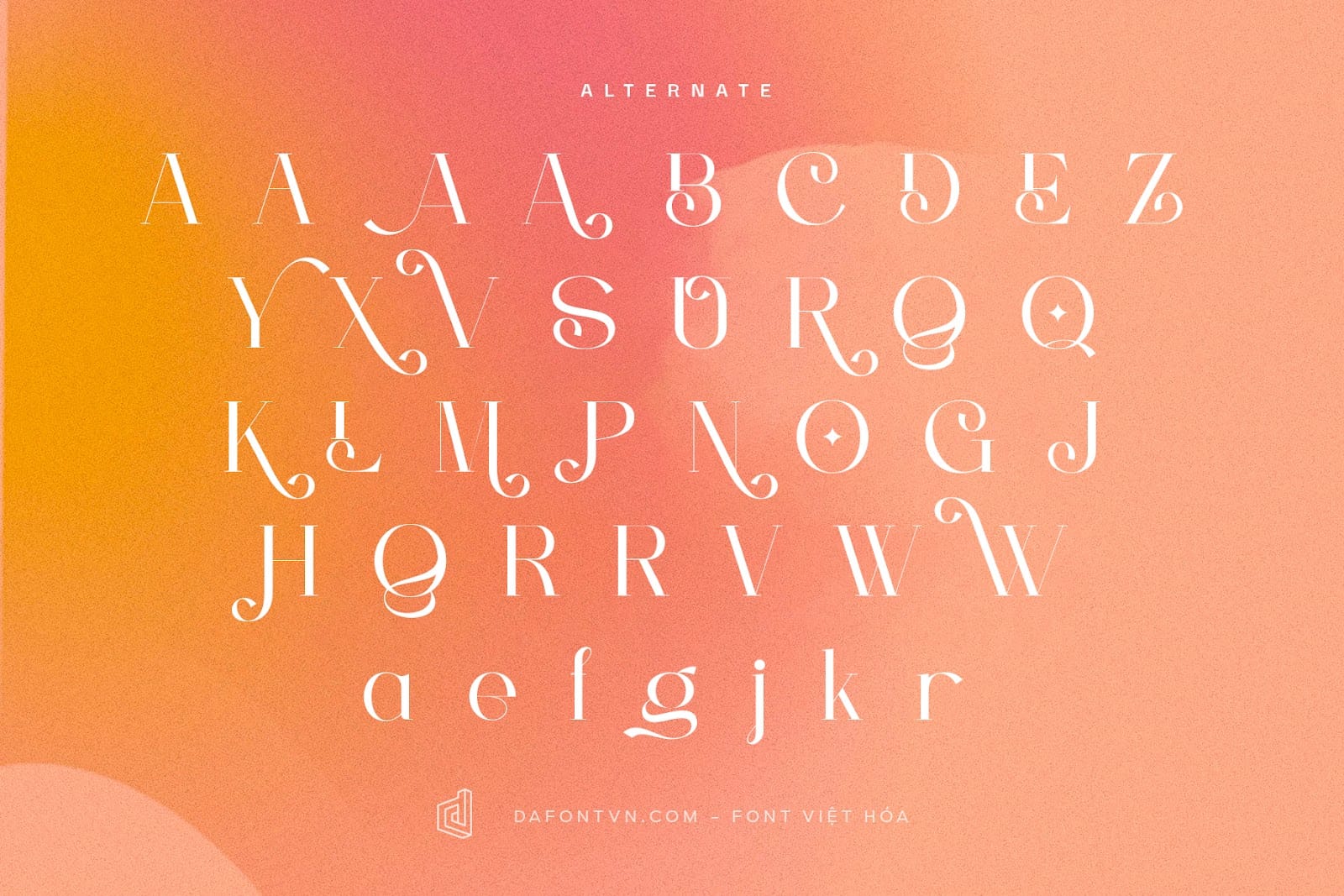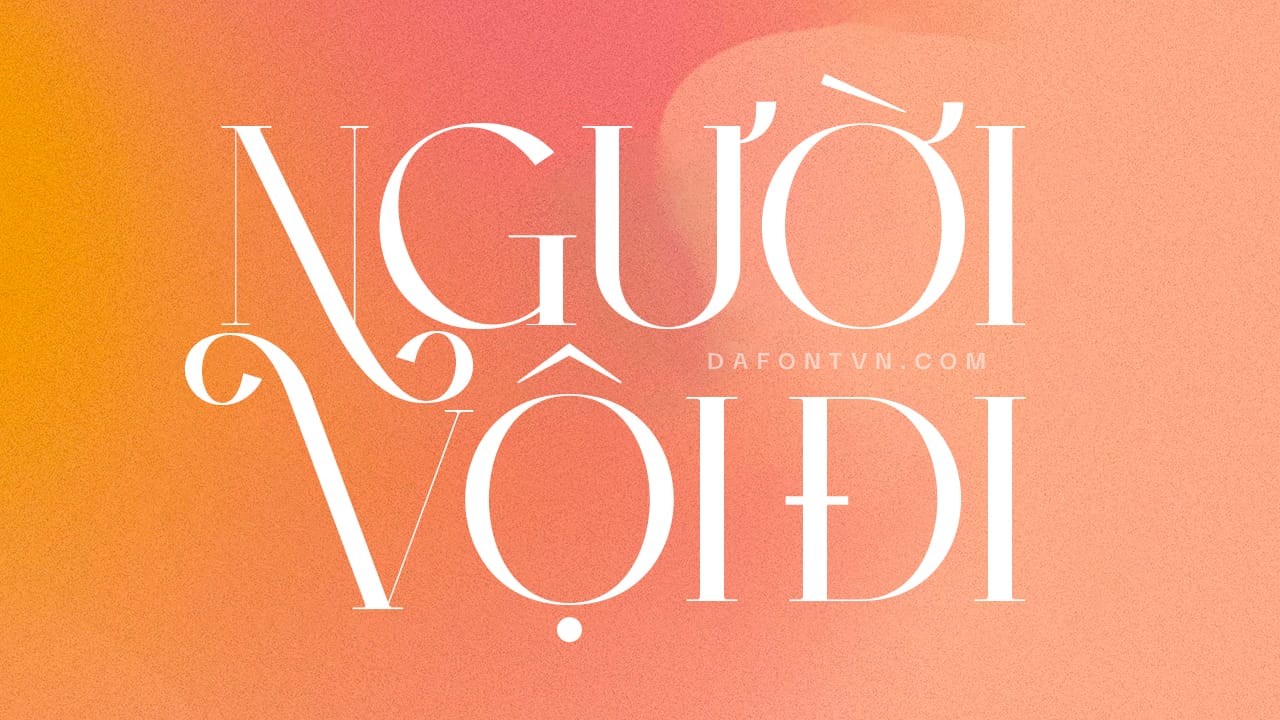
Font Berfilem là 1 kiểu serif theo phong cách hợp thời trang, thanh lịch, nghệ thuật, sang trọng và hiện đại cho phù hợp cho rất nhiều dự án của bạn.
Berfilem với các đường nét được thiết kế hiện đại dễ dàng áp dụng cho nhiều phong cách khác nhau như xây dựng thương hiệu, thiết kế logo, tiêu đề trang web, typography, thiệp mời. Nếu bạn đang tìm kiếm 1 kiểu font ấn tượng, độc đáo thì hãy thử font nhé Berfilem. Font hiển thị tốt ở cả tiêu đề hoặc văn bản. Ngoài ra, font đi kèm với nhiều chữ ghép và thay thế để bạn tha hồ sáng tạo.